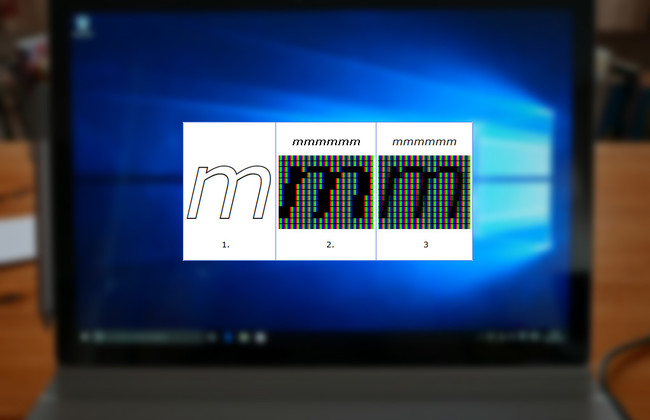
Si eres alguien bastante quisquilloso o que pone mucha atención al detalle, quizás alguna vez hayas notado que las tipografías en Windows tienden a verse más delgadas y menos "perfectas" o "suaves" de lo que se ven por ejemplo en un dispositivo móvil moderno con Android o iOS. Quien haya usado otros sistemas operativos de escritorio como Linux o mac OS, probablemente también haya notado que el texto en estos últimos se ve mejor.
Microsoft usa en Windows un sistema de renderizado para el texto llamado ClearType. Este está diseñado para que el texto sea más claro, nítido y fácil de leer, y de hecho lo es. Pero, esto no quiere decir que a otros les guste más el estilo de otros sistemas operativos. Para esas personas existe una herramienta llamada MacType, que cambia el perfil de las tipografías en Windows por uno más suave.
En mac OS el texto busca parecerse más al impreso y por eso se ve más suave. En Windows se le da prioridad a la claridad del texto, algo que lo hace más fácil de leer aún en tamaños muy pequeños, pero menos agradable para ciertos gustos.
MacType es una aplicación open source creada por un japonés y cuyo único objetivo es hacer que el texto en Windows se vea como el de Mac. Funciona en Windows 10 y todas las versiones anteriores hasta XP.
Lo siguiente es seleccionar un perfil de texto. El que se aplica por defecto si no lo cambias, es el mismo que usan las tipografías en Mac desde el 2010. Tienes otras opciones, incluso una para que el texto se vea como en iOS, o puedes añadir un nuevo perfil.
Dejo un ejemplo del cambio en el texto en la ventana del explorador de Windows de mi ordenador. Es algo sumamente sutil, pero si te interesó este tema en primer lugar, seguro lo notas con facilidad.